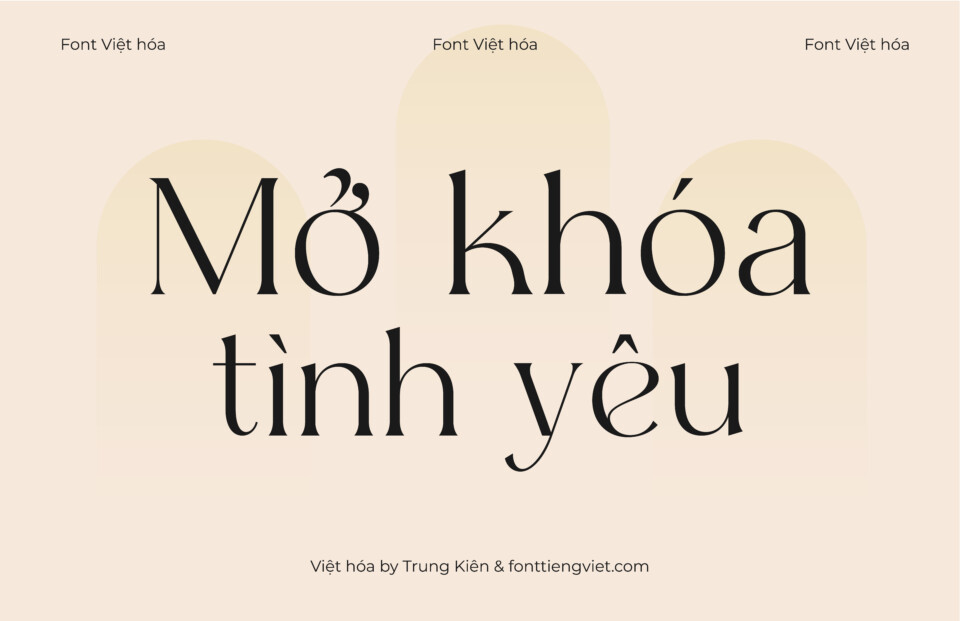
Trong thế giới sáng tạo, việc lựa chọn một Font Chữ phù hợp đóng vai trò then chốt giúp truyền tải thông điệp một cách hiệu quả nhất. Font Việt hóa 1FTV VIP Ergisa nổi lên như một sự lựa chọn hoàn hảo cho những ai đang tìm kiếm sự kết hợp giữa nét cổ điển và hơi thở hiện đại. Đây là bộ font serif (có chân) mang phong cách thanh lịch, giúp các bản thiết kế trở nên chuyên nghiệp và thu hút hơn bao giờ hết. Đặc biệt, phiên bản này đã được tối ưu hóa hoàn toàn cho tiếng Việt, giúp người dùng thoải mái sử dụng mà không lo lỗi hiển thị hay thiếu ký tự.
Đặc điểm nổi bật của Font Việt hóa 1FTV VIP Ergisa
Thiết kế tinh tế và đẳng cấp
Font Việt hóa 1FTV VIP Ergisa sở hữu những đường nét mảnh mai nhưng vô cùng chắc chắn. Các chân chữ được gọt giũa tỉ mỉ, tạo nên một tổng thể hài hòa và sang trọng. Font chữ này cực kỳ phù hợp cho các dự án thiết kế nhận diện thương hiệu, bìa tạp chí, thiệp mời đám cưới hoặc các ấn phẩm quảng cáo thời trang cao cấp. Sự cân bằng giữa các khoảng cách chữ giúp người xem dễ dàng tiếp nhận thông tin một cách tự nhiên và thoải mái nhất.
Khả năng ứng dụng đa dạng
Không chỉ giới hạn trong các thiết kế in ấn, Font Việt hóa 1FTV VIP Ergisa còn phát huy thế mạnh trong lĩnh vực thiết kế web và truyền thông mạng xã hội. Với bộ ký tự đa dạng và các tính năng Opentype thông minh, bạn có thể biến tấu các tiêu đề (heading) trở nên nổi bật hoặc tạo ra những đoạn trích dẫn giàu cảm xúc. Đây thực sự là công cụ đắc lực cho các bạn học sinh, sinh viên và những nhà thiết kế trẻ tại Việt Nam.
Để tận dụng tối đa vẻ đẹp của Font Việt hóa 1FTV VIP Ergisa, bạn nên kết hợp nó với các font không chân (sans-serif) đơn giản để tạo sự tương phản. Khi trình bày nội dung bài học hoặc dự án cá nhân, hãy đảm bảo kích thước chữ đủ lớn để các nét chân thanh mảnh được hiển thị rõ nét nhất. Hãy tải ngay Font Miễn Phí, Font Việt Hóa, Font Việt hóa 1FTV VIP Ergisa để làm mới kho tài nguyên sáng tạo của mình ngay hôm nay.